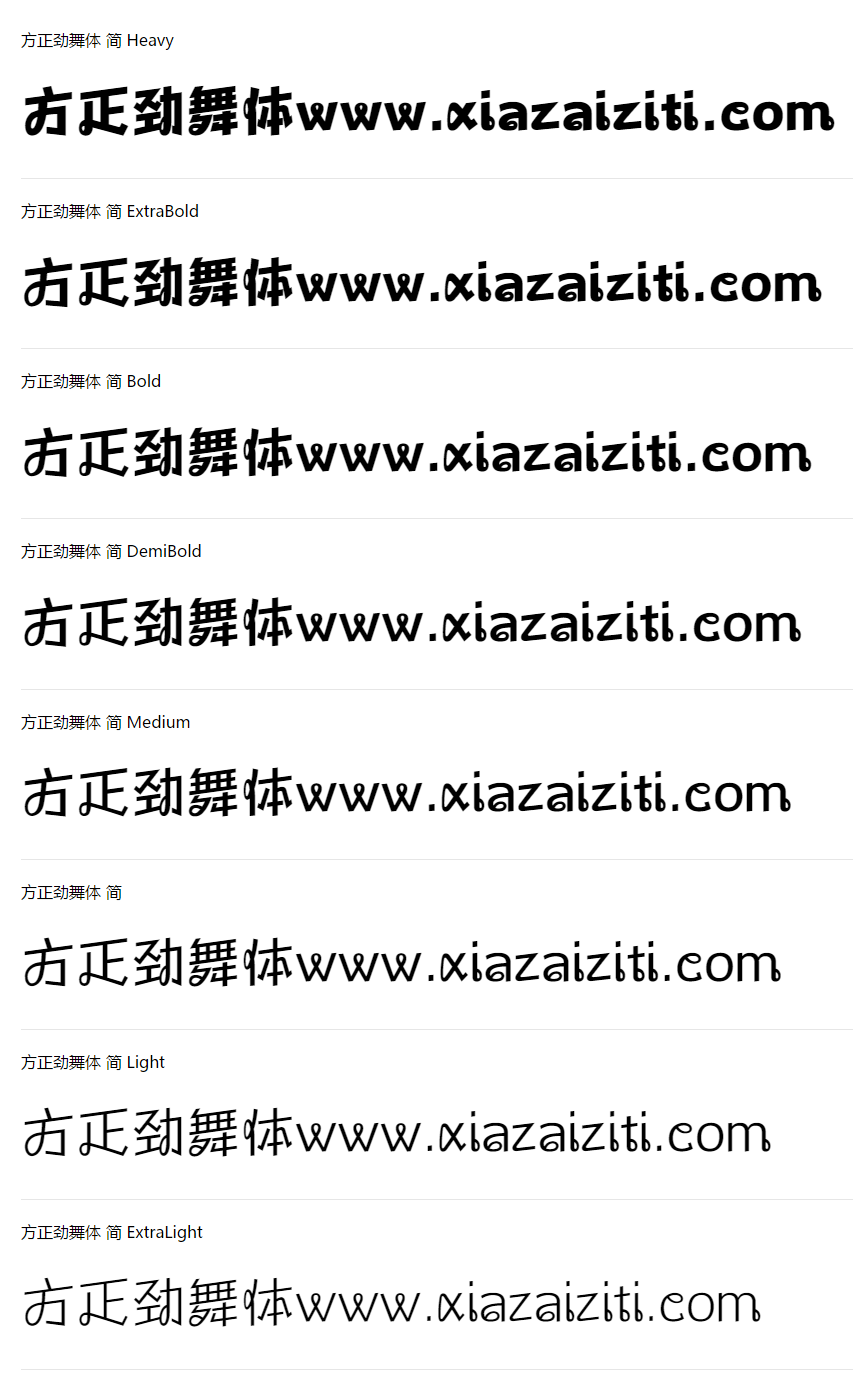
方正勁舞體,該款字體參考了行書基礎結構進行創意設計,融入了黑體的簡潔,造型特異,充滿現代感。撇、捺間帶有明顯的折角,凸顯該字體的簡潔有力的個性,字體帶有蜷曲的裝飾性飾角,其風格隽秀大方,適用于商業廣告以及包裝設計當中。品牌: 方正字庫設計師: 郭炳權發行時間:2018字庫編碼:大陸簡體(GB2312-80)關鍵詞:創意字體、系列字體、特粗的、最新字體方正勁舞體